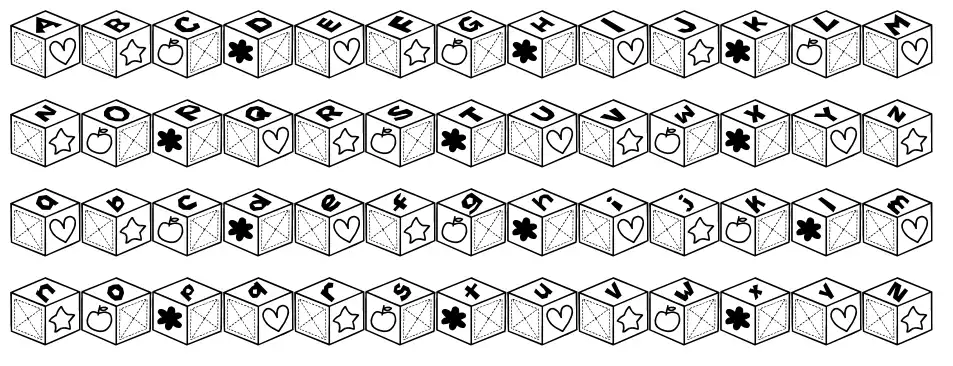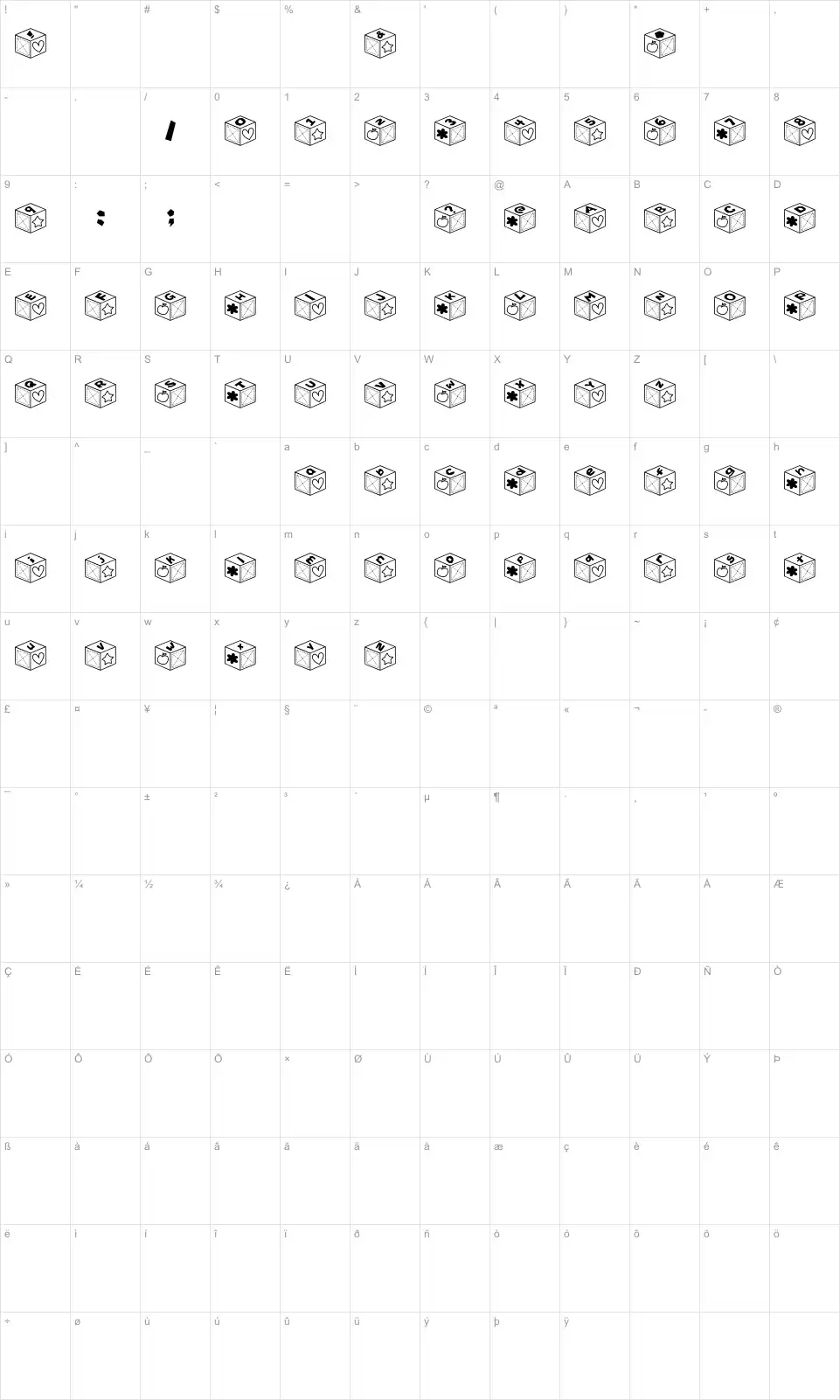
A fonte Sai Font, criada pelo designer Pi’s Room, é uma opção incrível para quem busca adicionar um toque peculiar e sofisticado a seus projetos gráficos. Com sua categoria Fancy e categoria Decorative, essa font oferece um charme único que certamente dará um novo brilho a qualquer projeto. Se você está procurando por uma fonte divertida e inovadora, a Sai Font é um investimento valioso. Se você já está convencido, não hesite em baixar o arquivo TTF ou gerar um preview personalizado de texto online para ver como ela se destaca. Com uma categoria Fancy e adotada desde 2022, já estão muitos usuários satisfeitos com esta font. Em tamanho de 10 KB, ela é compacta e fácil de usar, tornando-a perfeita para projetos no seu computador. Com seus downloads de 1463, é evidente que esta font já se destacou na comunidade de designers. Por isso, é uma escolha atraente para quem busca uma fonte divertida e inovadora para seu projeto.
Categoria: Fancy › Decorative
Designer: Pi’s Room